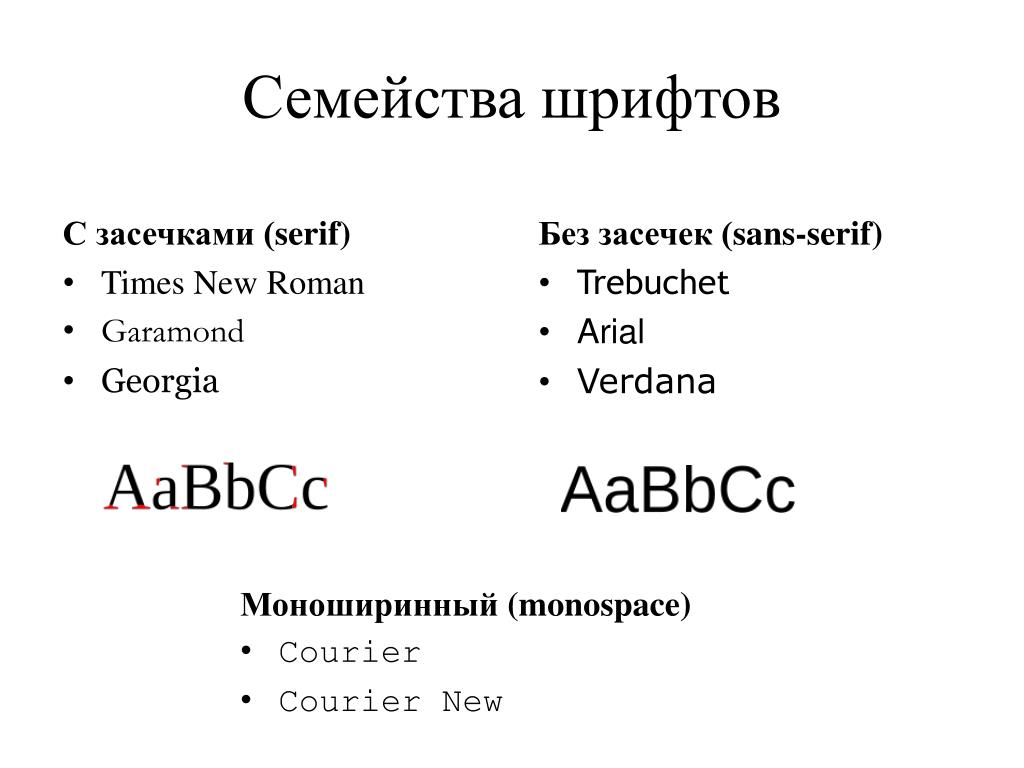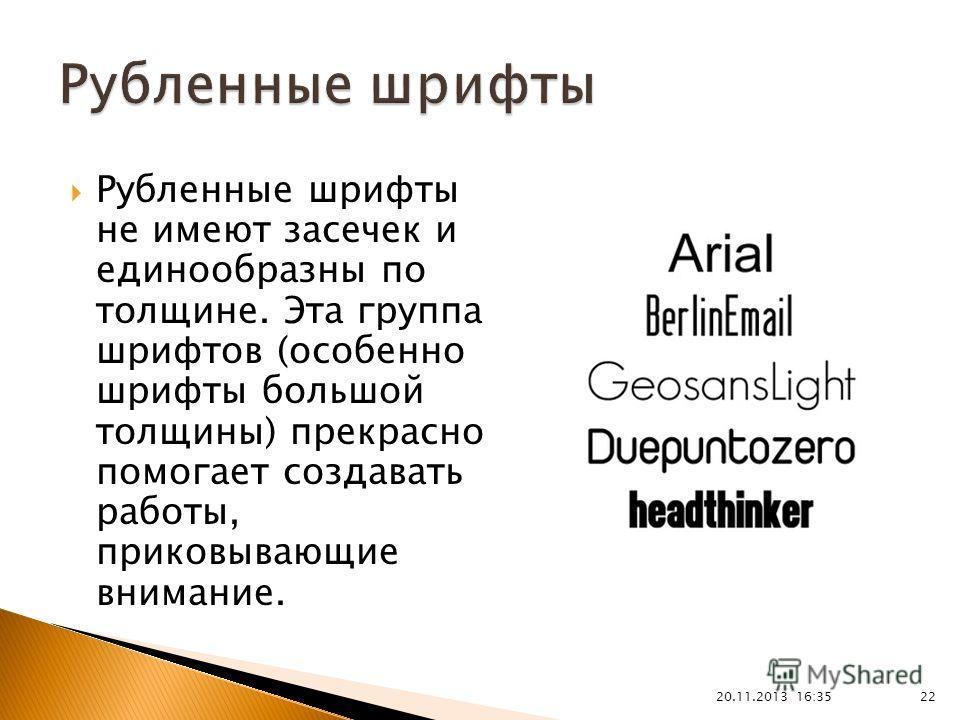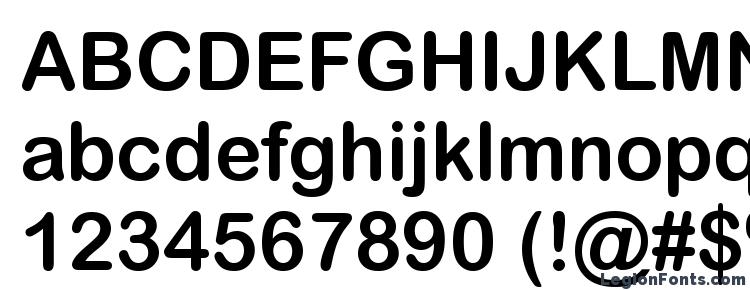
10 недооцененных бесплатных Google шрифтов без засечек
Google Fonts – огромный ресурс, но мы видим одни и те же шрифты в тысячах проектов.
В этой статье предлагаем вам тщательно отобранный список из 10 привлекательных, но мало используемых шрифтов без засечек, которые доступны бесплатно в библиотеке шрифтов Google.
1. DM Sans
Дизайнеры: Colophon Foundry, Jonny Pinhorn, Indian Type Foundry
Описание: DM Sans – это малоконтрастный геометрический шрифт без засечек, предназначенный для использования с меньшими размерами текста.
2. Lexend
Дизайнеры: Bonnie Shaver-Troup, Thomas Jockin, Santiago Orozco, Héctor Gómez
Описание: Lexend первоначально спроектирован с учетом читателей, страдающих дислексией и другими проблемами чтения. Он предназначен для снижения зрительного стресса и улучшения навыков чтения.
3. Chakra Petch
Дизайнер: Cadson Demak
Описание: Chakra Petch – квадратный шрифт без засечек с сужающимися углами, поддерживающий как тайский, так и латинский алфавит.
4. IBM Plex Sans
Дизайнеры: Mike Abbink, Bold Monday
Описание: IBM Plex Sans – нейтральный, но дружелюбный гротеск без засечек, входящий в суперсемейство IBM Plex (содержащие также IBM Plex Serif и IBM Plex Mono).
5. Space Grotesk
Дизайнер: Florian Karsten
Описание: Space Grotesk – это вариант пропорционального шрифта без засечек, основанный на семействе шрифтов фиксированной ширины Space Mono от Colophon Foundry.
6. Balsamiq Sans
Дизайнер: Michael Angeles
Описание: Balsamiq Sans – это рукописный шрифт без засечек, изначально созданный для инструмента создания вайрфреймов Balsamiq.
7. Questrial
Дизайнеры: Joe Prince, Laura Meseguer
Описание: Questrial – это геометрический шрифт без засечек с добавлением гротескного оттенка.
8. Epilogue
Дизайнеры: Tyler Finck, ETC
Описание: Epilogue представляет собой переменный шрифт без засечек с осью веса, девятью весами и курсивом.
9. Archivo
Дизайнеры: Héctor Gatti, Omnibus Type
Описание: Archivo – гротескный шрифт без засечек, напоминающий американские шрифты конца девятнадцатого века.
10. Sen
Дизайнер: Kosal Sen
Описание: Sen – это шрифт без засечек геометрической формы с разумным и дружелюбным внешним видом.
Самые популярные шрифты без засечек
Источники Sans Serif — это те, которые мы видели во многих фильмах и даже крупные бренды используют его. Но не только это, семейство по преимуществу занимает те большие абзацы, которые мы видим на экране мобильного устройства или ПК.
Поэтому мы покажем вам лучшие шрифты без засечек и объясним, почему они так называются. или даже происхождение его имени. Мы узнаем те источники, как Futura, которые можно увидеть даже на Луне, когда НАСА использовало их в свое время. Действуй.
Что такое шрифт без засечек
Если мы зайдем в Википедию, то обнаружим, что шрифт без засечек Это без изящества или сухого письма. То есть у каждого символа отсутствуют так называемые маленькие засечки или засечки; какие орнаменты обычно располагаются на концах строк символов.
Этот шрифт обычно можно использовать для заголовков и отсутствие засечек или засечекесли смотреть на нее с точки зрения читателя, заставляет наши глаза гораздо больше напрягаться, когда нам приходится читать большие блоки текста.
Но, конечно, если мы перейдем на цифровой формат и будем читать через экраны, такие как мобильные устройства, планшеты или устройства чтения, за счет пикселизации достигается то, что без засечек выглядят намного яснее и чище, чем шрифты с засечками или засечками. Так что, если вы ищете идеальный шрифт для чтения с мобильного устройства, такого как целевые страницы или блоги, без засечек более чем идеален для больших блоков текста.
Между источниками самый популярный шрифт без засечек, который мы можем найти Helvetica, Avant Garde, Arial и Geneva. К шрифтам с засечками относятся Times Roman, Courier, New Century Schoolbook и Pataino.
Его четыре самые большие группы
мы имеем четыре основные группы без засечек:
- Гротеск— Гротескные шрифты имеют ограниченное изменение ширины штриха. Окончания кривых в основном горизонтальные и имеют буквы «G» и «R» со шпорами «изогнутой ножки». Вот некоторые примеры гротеска: Venus, News Gothic, Franklin Gothic и Monotype Grotesque.
ABeeZee — это открытый и удобный шрифт без засечек, разработанный Аней Майнерс. Он бывает двух основных стилей.
Folks — уникальный и забавный шрифт без засечек, разработанный Манфредом Кляйном Фонтерия. Он поставляется с четырьмя стилями, каждый из которых имеет разный вес шрифта.
Nunito — это округлый шрифт без засечек, разработанный Верноном Адамсом.